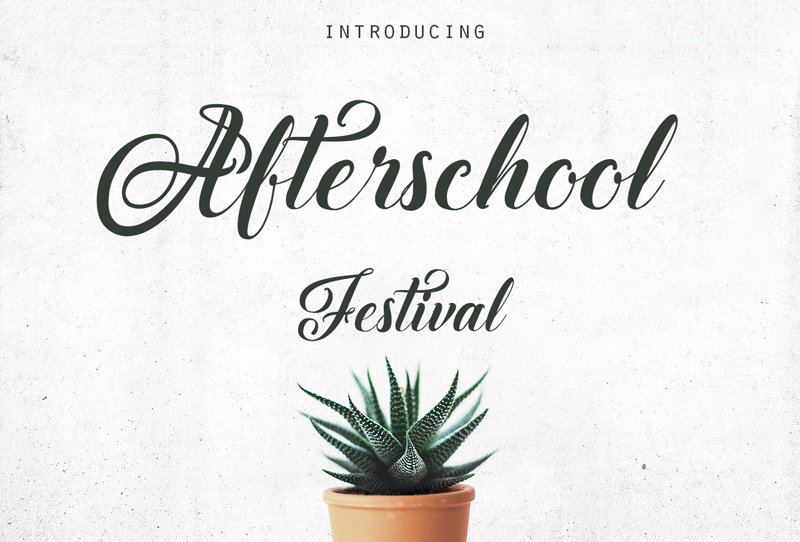
Afterschool Festival Font – Download Grátis
Afterschool Festival é uma fonte tipográfica desenvolvida pelo Octotype que traz a essência do festival escolar ao seu design. Com sua letra dinâmica e vibrante, esta fonte oferece uma maneira única de destacar seu trabalho em eventos culturais ou esportivos. Perfeita para designers e criadores de conteúdo buscando um estilo único para expressar seus designs, Afterschool Festival é ideal para o uso em materiais publicitários, cartazes, logotipos e mais. Com a disponibilização de fontes completas e licença comercial disponíveis através do endereço , os criadores podem usar essa fonte com confiança sem preocupações sobre direitos autorais. Seja para projetos grandes ou pequenos, Afterschool Festival vai fazer sua marca mais vibrante e memorável.